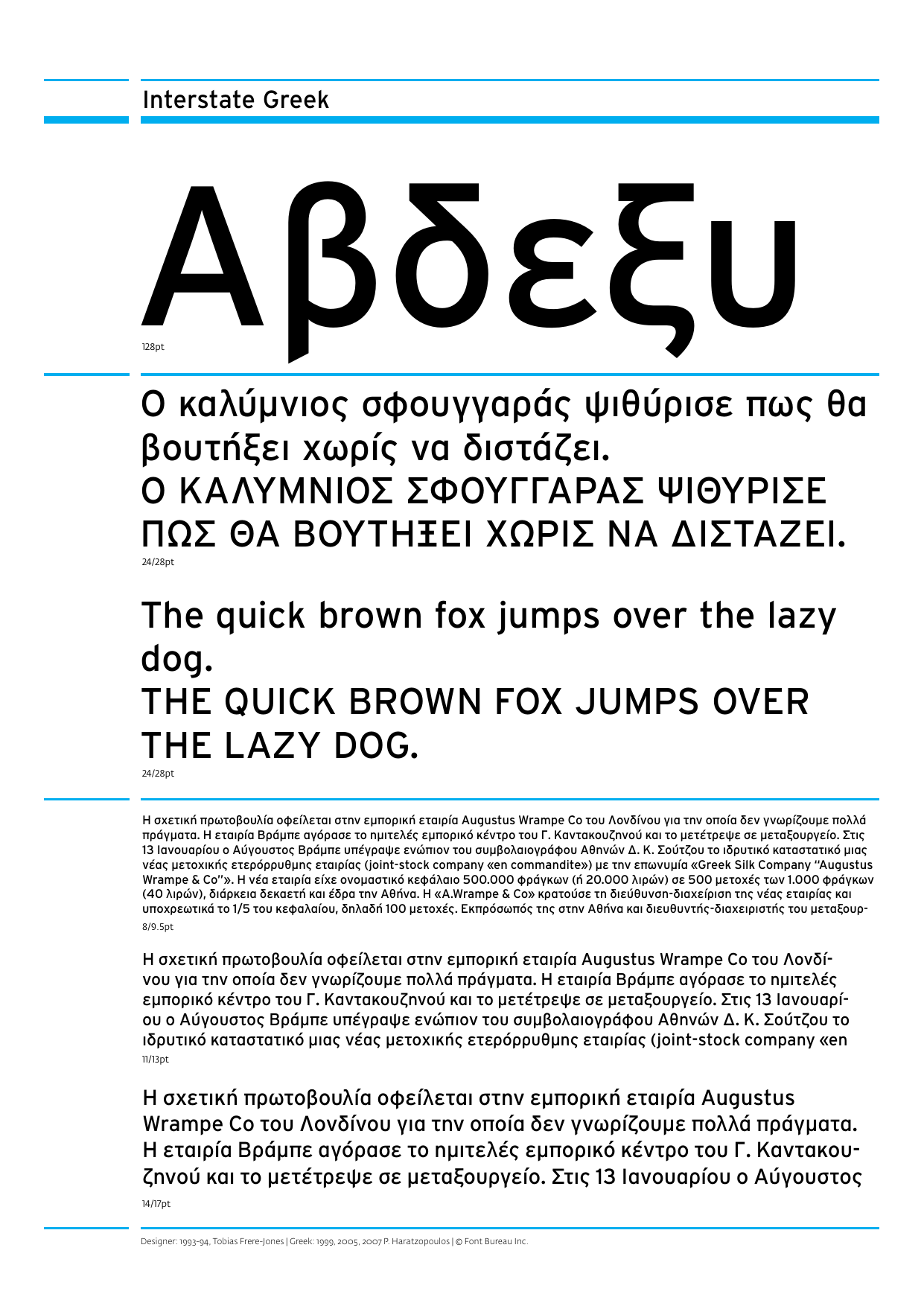
Interstate Ελληνικά
Είναι μία από τις δημοφιλέστερες γραμματοσειρές στον κόσμο και σχεδιάστηκε από τον Tobias Frere-Jones όντας εμπνευσμένη από τη γραμματοσειρά των Αμερικανικών αυτοκινητοδρόμων. Η ελληνική έκδοση σχεδιάστηκε αρχικά σε 4 βάρη για λογαριασμό της διαφημιστικής εταιρίας Y&R προκειμένου να χρησιμοποιηθεί και στην Ελλάδα, όπως και διεθνώς, από τη Citibank. Αργότερα επανασχεδιάστηκε και προστέθηκαν 6 νέα βάρη για να χρησιμοποιηθεί από τη διαφημιστική εταιρία Upset για τις ανάγκες της αεροπορικής εταιρίας Αegean.